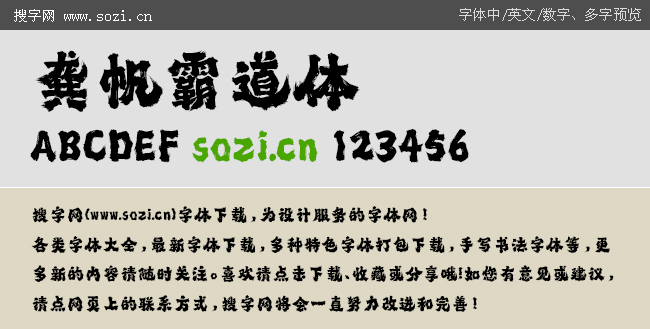
龔帆霸道體
搜字網(wǎng)給大家提供一款龔帆霸道體中文字體下載,該字體是一款非常個(gè)性的手寫(xiě)書(shū)法字體,字體書(shū)寫(xiě)時(shí)豪放大氣,字體邊緣帶有飛墨效果,給人一種霸氣十足的視覺(jué)感受,適用于平面宣傳設(shè)計(jì)、網(wǎng)頁(yè)設(shè)計(jì)、海報(bào)設(shè)計(jì)等應(yīng)用(淘寶搜龔帆字庫(kù)可買(mǎi)單字授權(quán))。